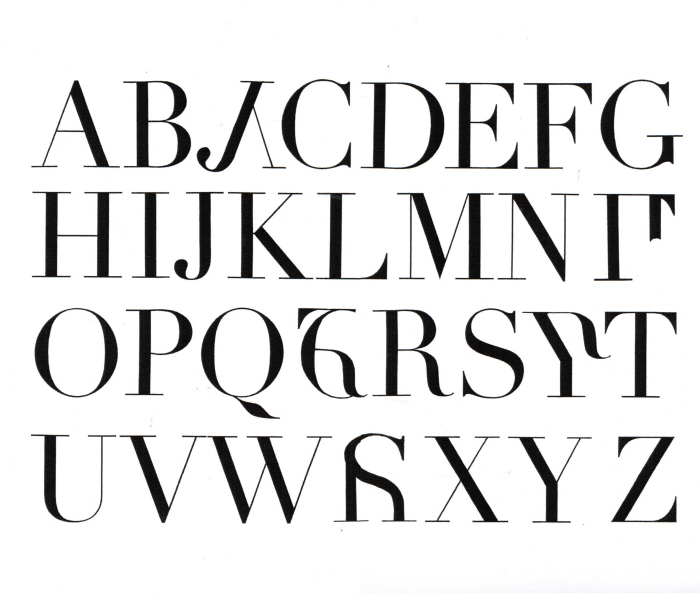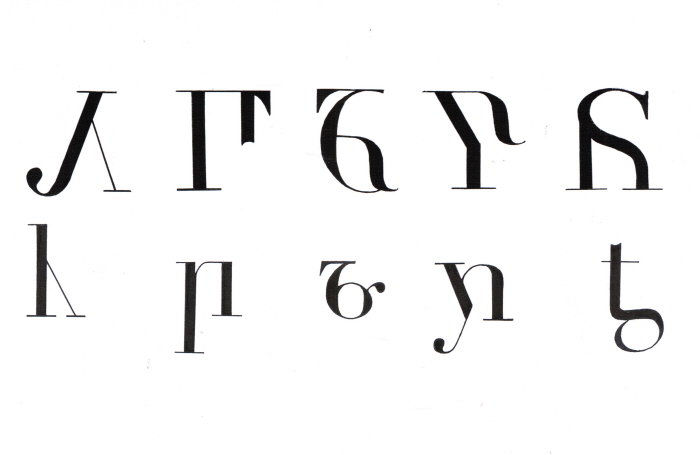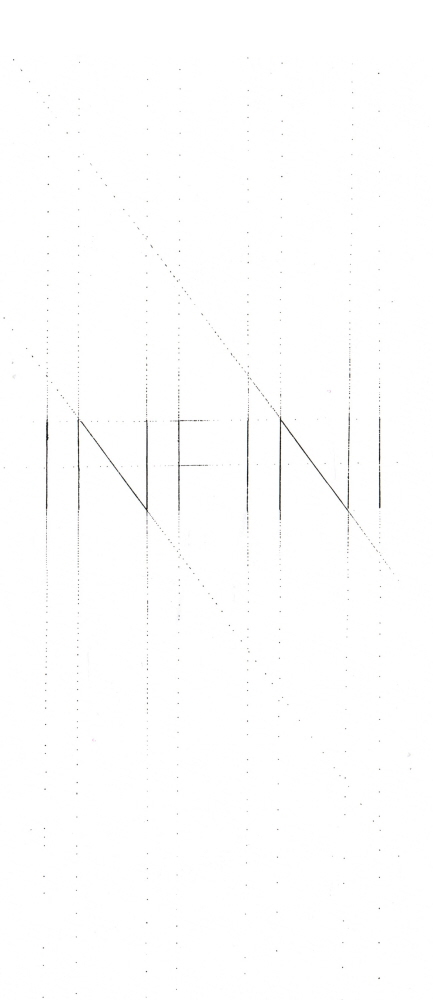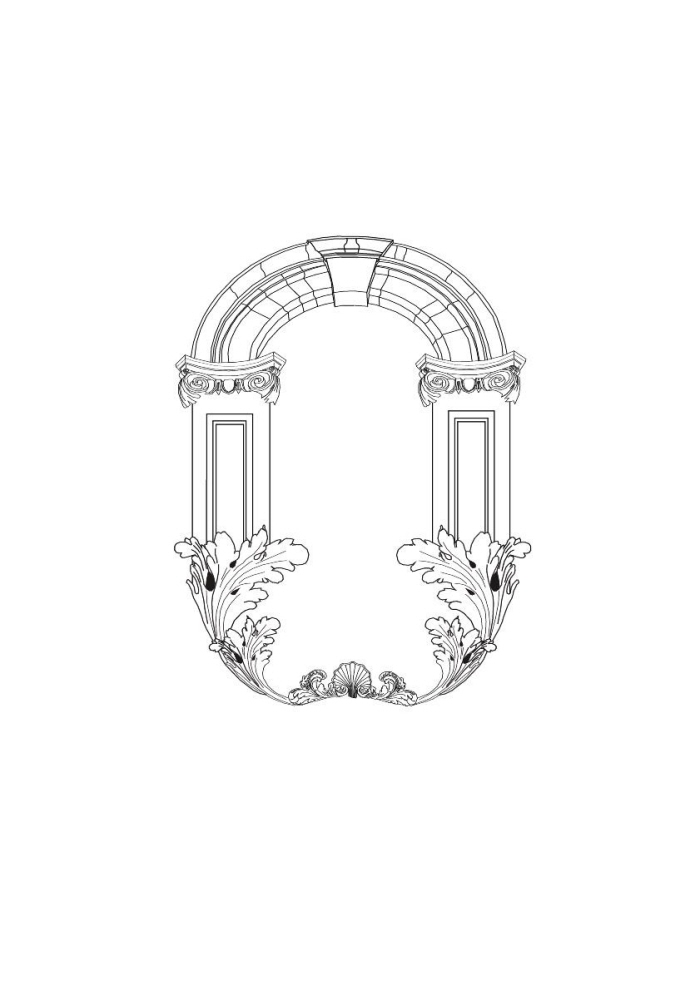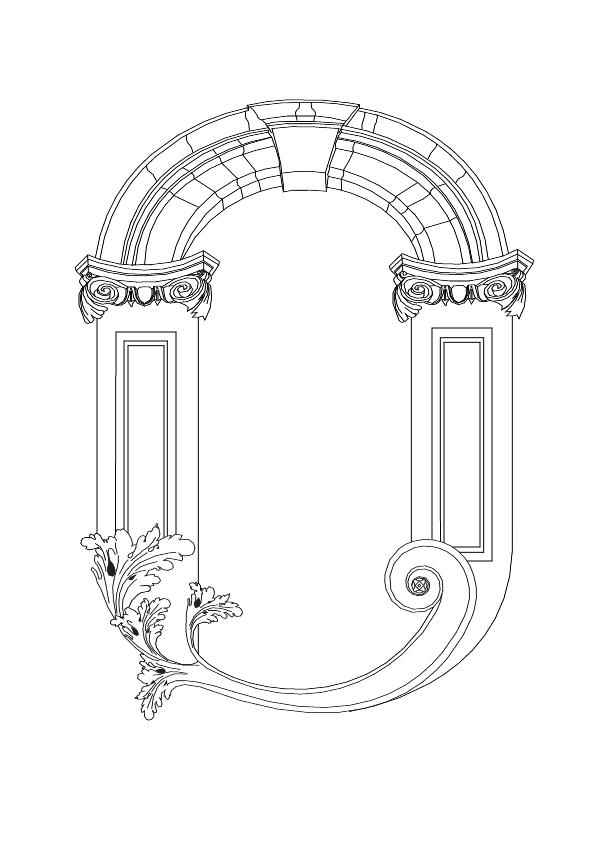
Jeu créatif sur le mot. Evolution
Jeu créatif sur le mot. Perturbation.
Jeu créatif sur le mot. Enfermement.
Jeu créatif sur le mot. Infini
Création d'une lettre Baroque. Illustrator.
Invention de caractère typographique à partir d'un alphabet existant, sans ordinateur. Travail de 1ere année.
Invention de caractère typographique à partir d'un alphabet existant sans ordinateur. Travail de 1ere année.